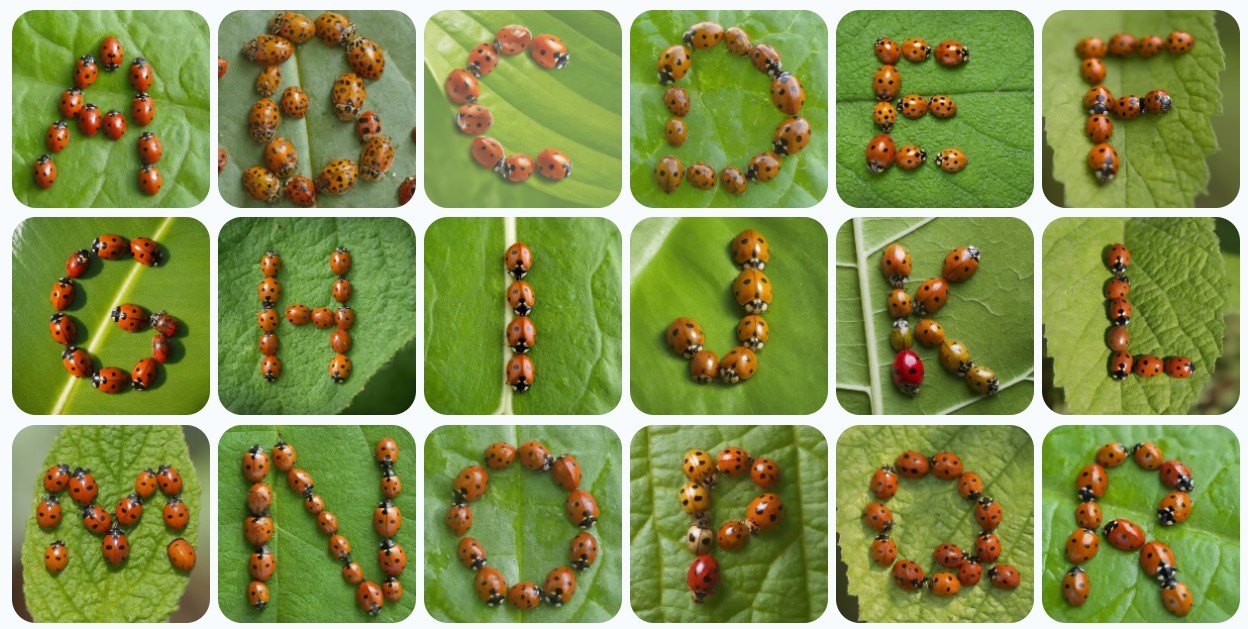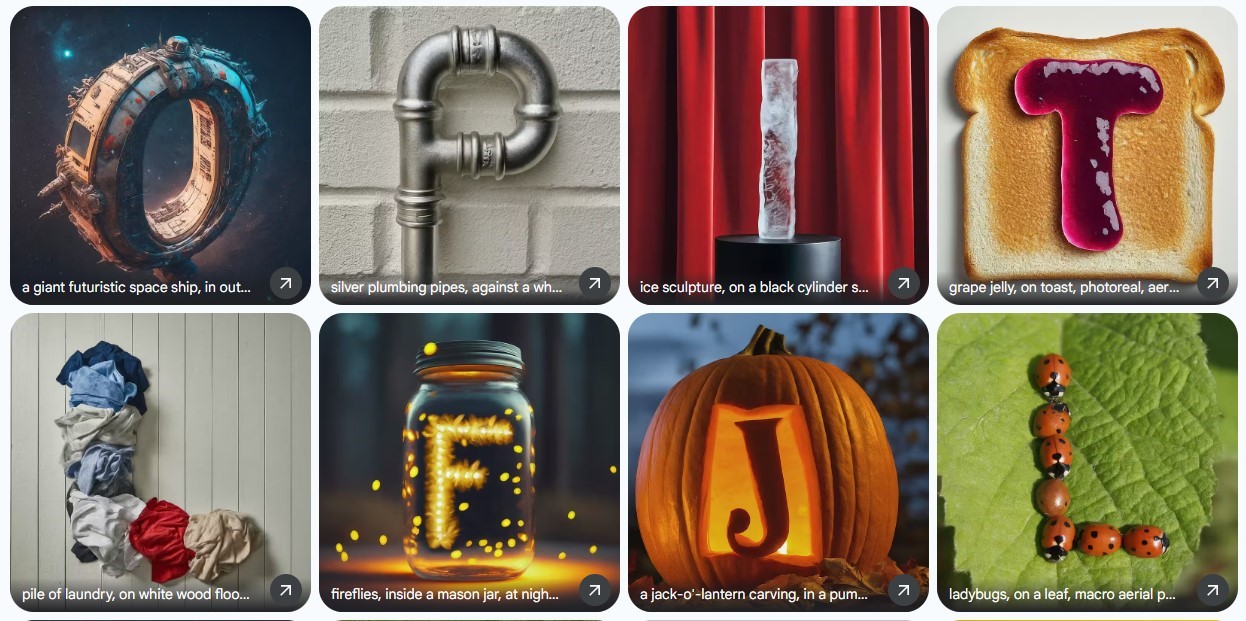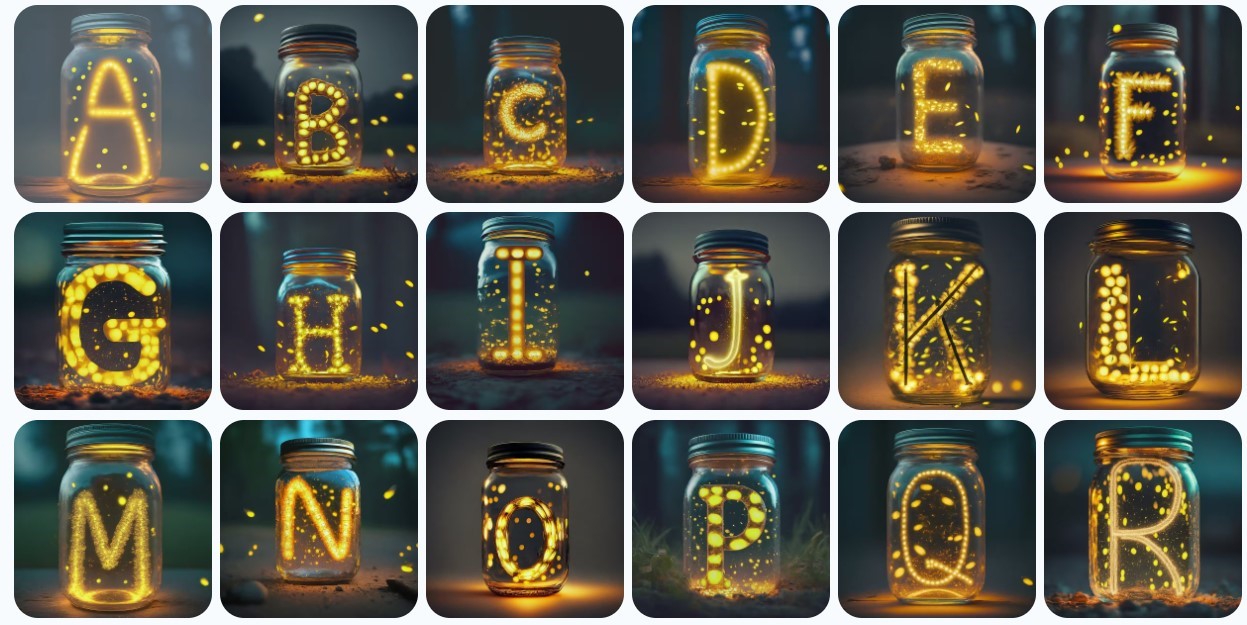
GenType: izradite svoj "font" uz Googlev zabavni servis
Zabavna primjena generativne umjetne inteligencije, koja nekima može biti i od koristi, dostupna je kao Googleov developerski eksperiment, a omogućava izradu atraktivnih vizuala
Dizajnirate li pozivnice za dječje rođendane ili neke slične vizuale, pa želite imati jedinstven font prilagođen samo određenoj posebnoj prilici, ovaj servis mogao bi biti prava stvar za vas. Google je u obliku eksperimenta objavio alat GenType, pokretan (a kako drugačije) generativnom umjetnom inteligencijom.
U njega je potrebno upisati tek opis vizuala koji želite vidjeti, kao da izrađujete ilustraciju u bilo kojem difuzijskom GenAI modelu. No, ono što ćete kao rezultat dobiti nije jedna ilustracija, već njih 26 – za svako slovo engleske abecede. Bubamare na lišću, olovke i gumice na stolu, vodovodne cijevi, kabeli, zviježđa – bilo što da mu zadate, GenType će pretvoriti u cijeli "font" u istom stilu.
Svako od dobivenih slova moguće je generirati i iznova, za slučaj da vam se ne dopadne prvi prijedlog, a slike je potom moguće i potpuno esplatno preuzeti u punoj rezoluciji (jedno slovo veličine je 800x800 točaka). Zabavno, korisno, kreativno i besplatno – što vam više treba?